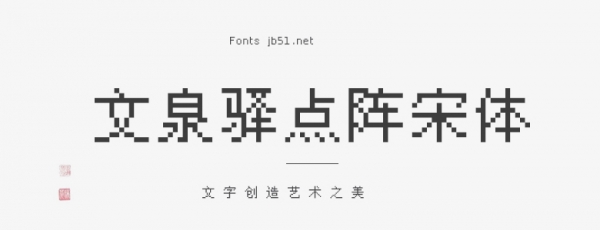
文泉驛點(diǎn)陣宋體是一個(gè)”自由中文字體”。該字體包含了所有常用簡(jiǎn)體中文、繁體中文,日文及韓文所需要的漢字(最新版本包含超過(guò)27842個(gè)漢字,完整覆蓋GB2312/Big5/GBK/GB18030標(biāo)準(zhǔn)字符集)。該字體同時(shí)還包含了英文、日文、韓文和其他多種語(yǔ)言符號(hào)。該點(diǎn)陣字體包含五個(gè)屏幕常用字號(hào)(9pt-12pt),逾21萬(wàn)漢字點(diǎn)陣,這些點(diǎn)陣都經(jīng)過(guò)參與者和組織者的精心設(shè)計(jì)和調(diào)整,手工優(yōu)化后的漢字點(diǎn)陣顯示清晰銳利,特別易于屏幕閱讀使用。
此為娛樂(lè)部以文泉驛點(diǎn)陣宋體 v1.0.0-RC1 的 PCF 字體制作的 TTF 版字體。希望可以給中文的點(diǎn)陣字體和像素字體增加一個(gè)新的選擇。